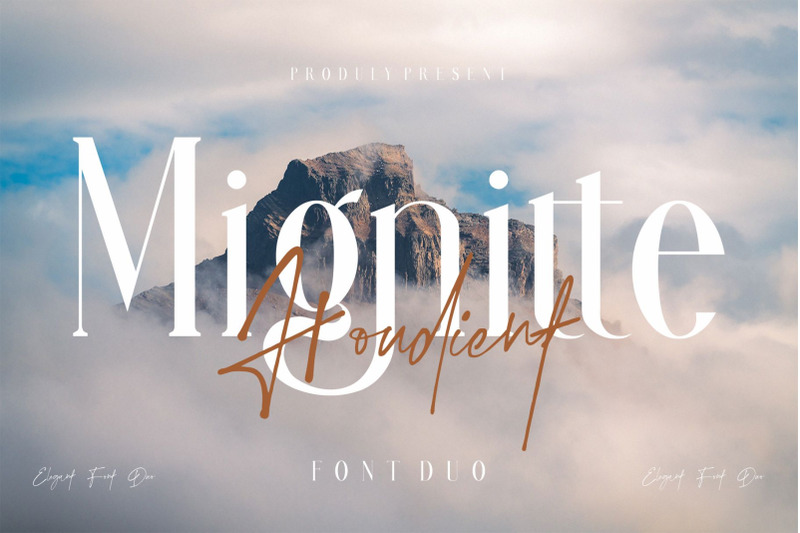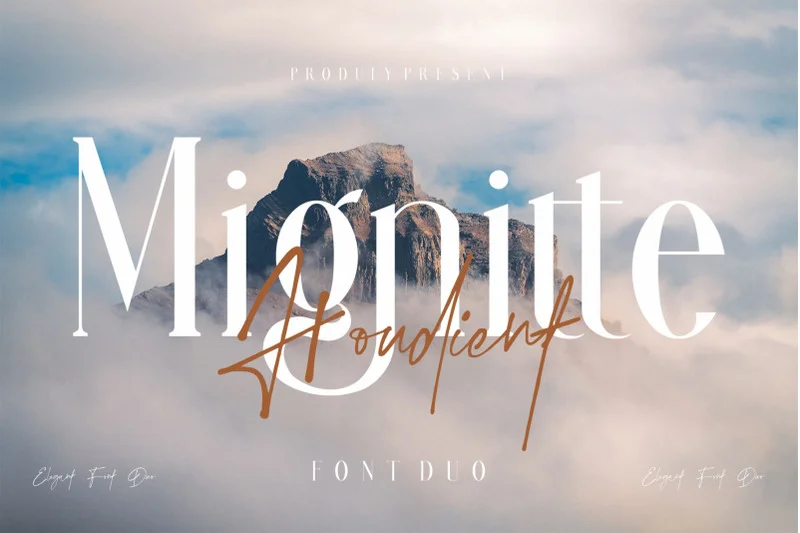
Название: Mignitte & Houdient Duo Font (2021)
Mignitte & Houdient Signature - стильный дуэт шрифтов Serif, вдохновленный знаменитым минималистским логотипом, идеально подходит для оформления шаблонов, брошюр, видео, рекламного брендинга, логотипов и многого другого.
Название: Mignitte & Houdient Duo Font (2021)
Mignitte & Houdient Signature - стильный дуэт шрифтов Serif, вдохновленный знаменитым минималистским логотипом, идеально подходит для оформления шаблонов, брошюр, видео, рекламного брендинга, логотипов и многого другого.